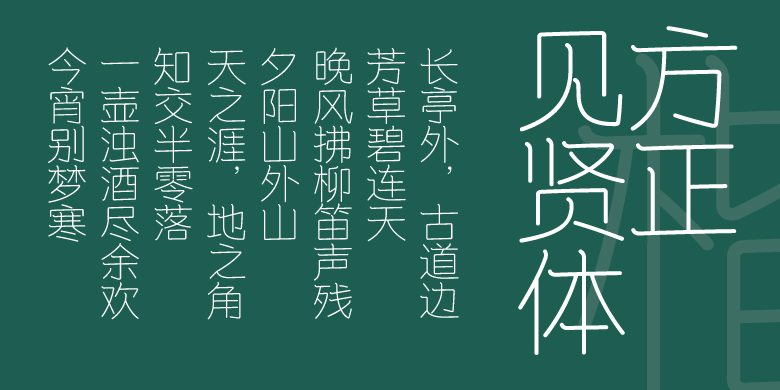
方正见贤体
《见贤体》是几年前方正字库曾经以小学教科书体为方向的命题的方正奖(第八届)字体比赛作品。当时大多数参赛设计师均采用了毛笔楷书为基础的设计字样。鉴于作者自身的经历和经验对于这个主题有了自己的见解和设计原则,考虑到小学低年级的书写能力和工具限制,作者选择“等线”楷书表现。名称是字库比赛字样中的一个非常适合的词汇。非常庆幸这个尝试得到了评委们的初步认可,获得了优秀奖。虽然时间过去很久,但内心依然有着表达这个想法的愿望,希望得到更多人的认同。